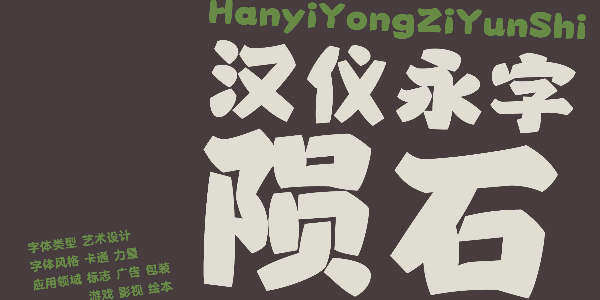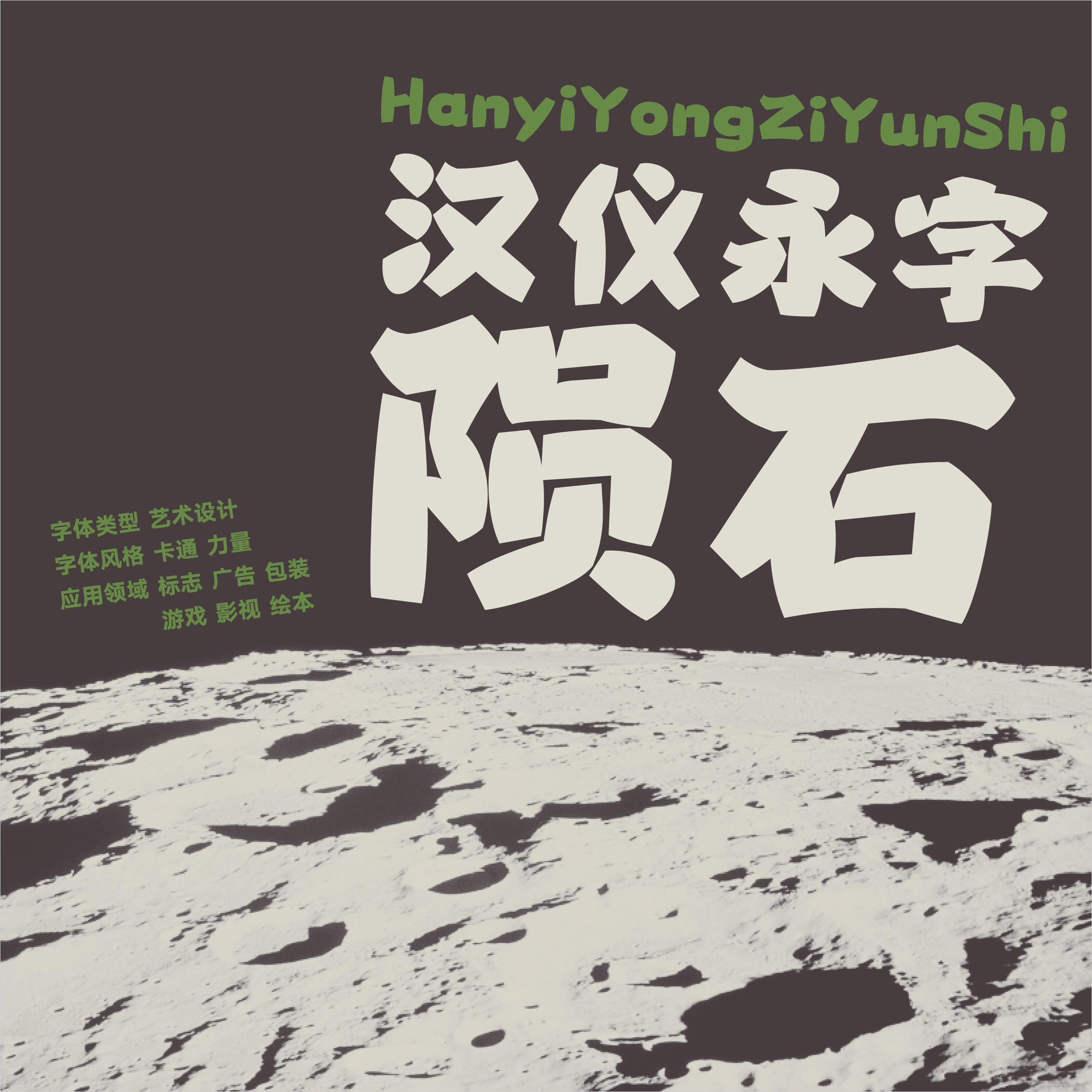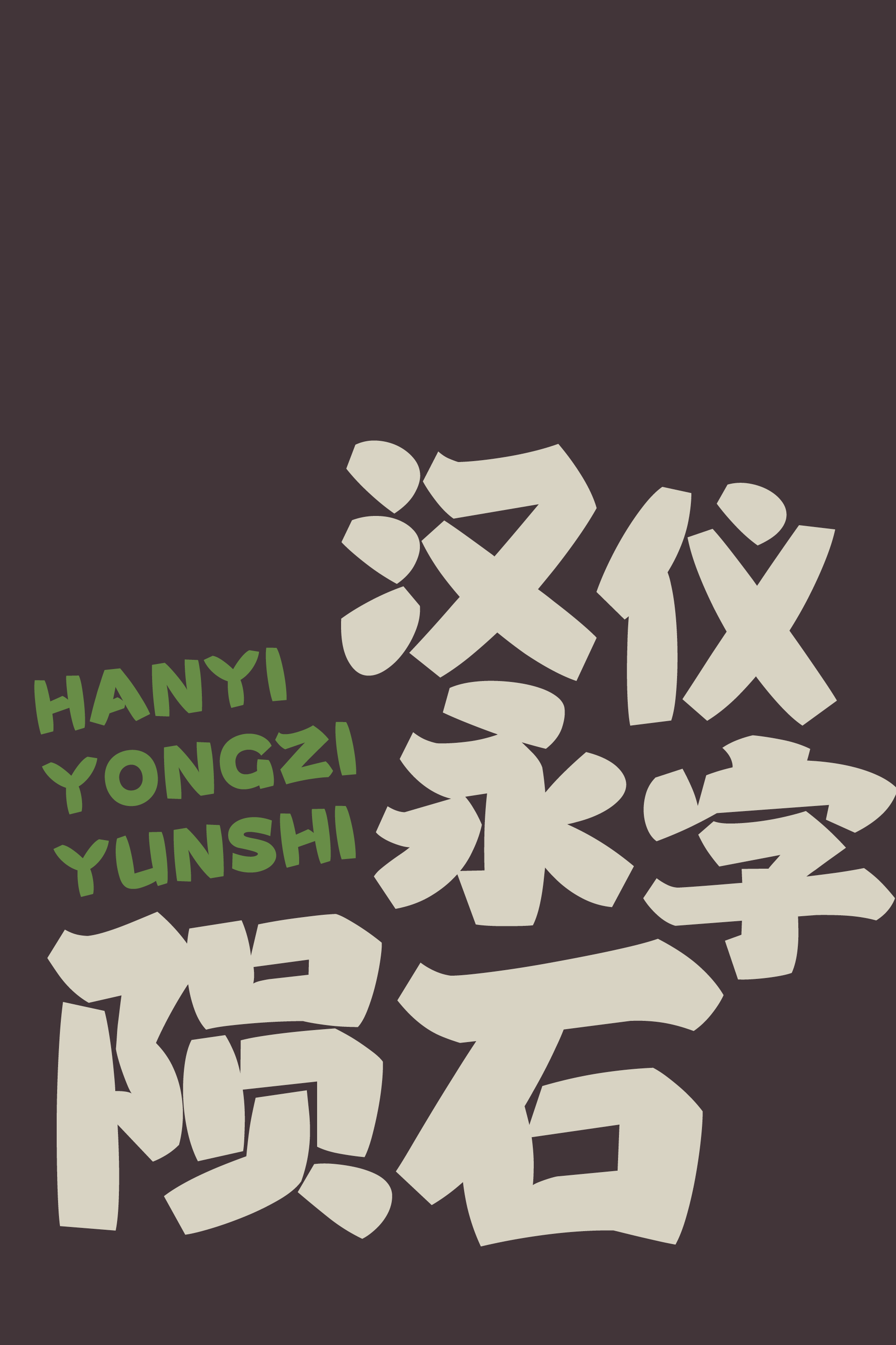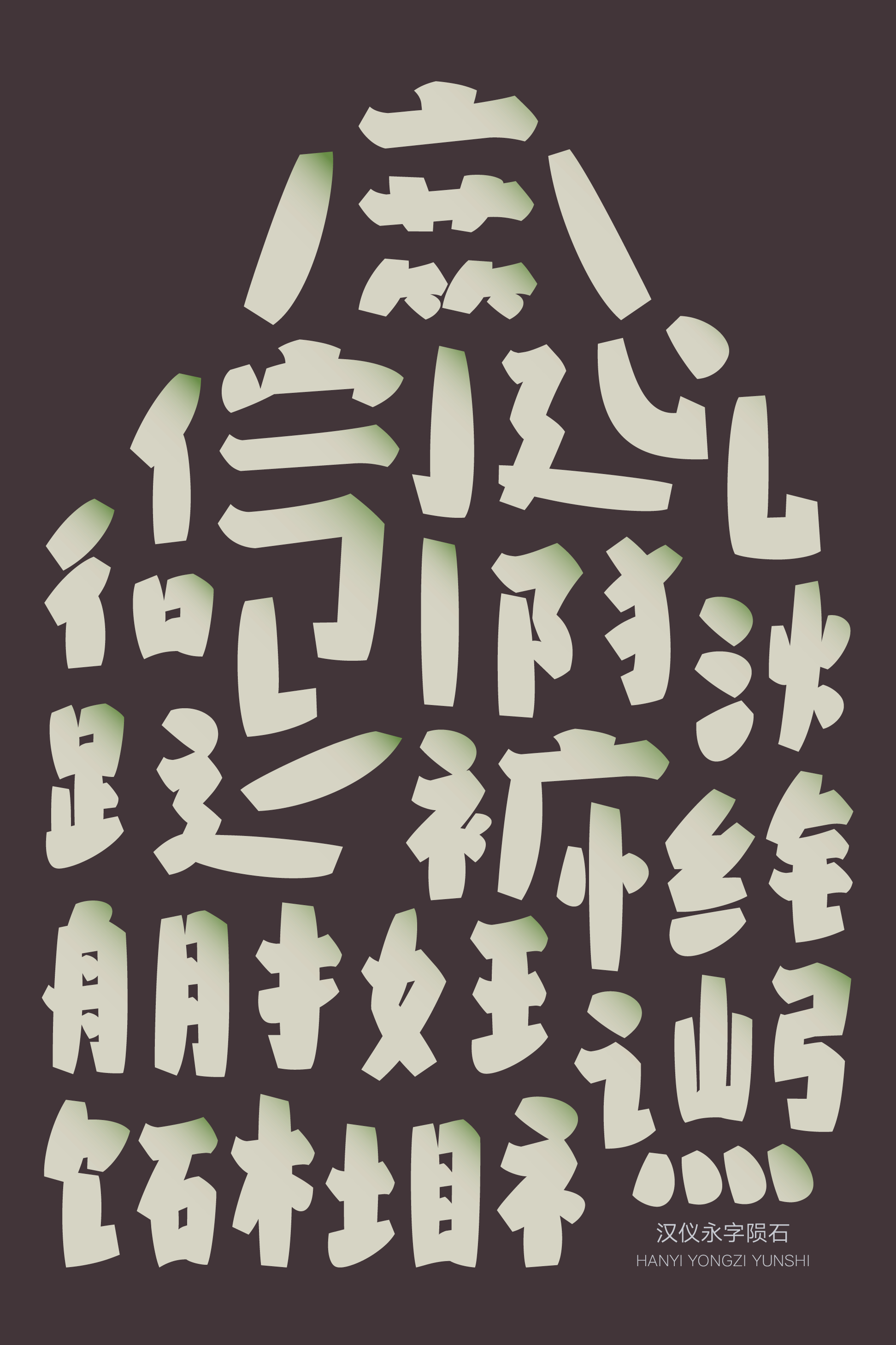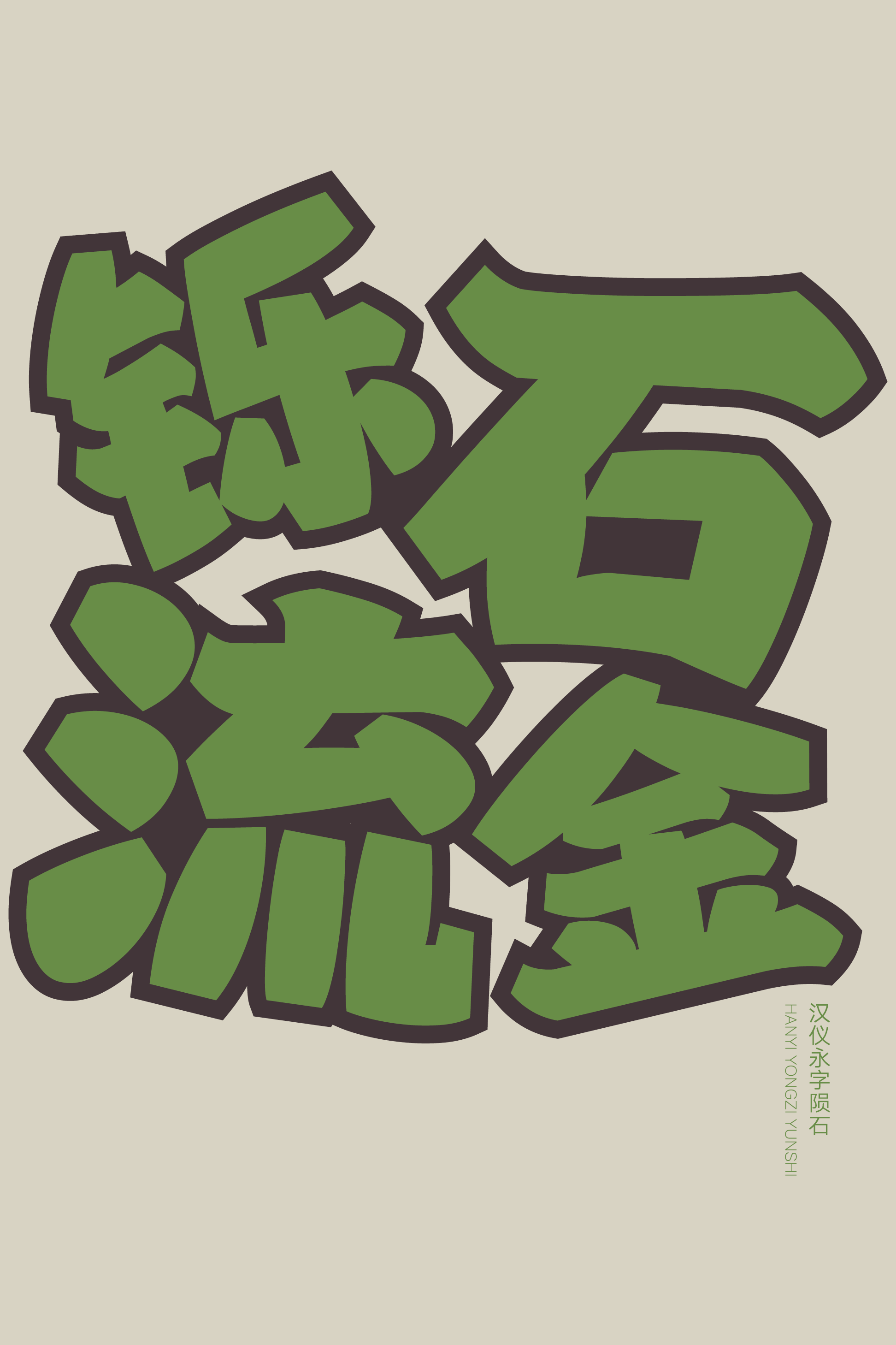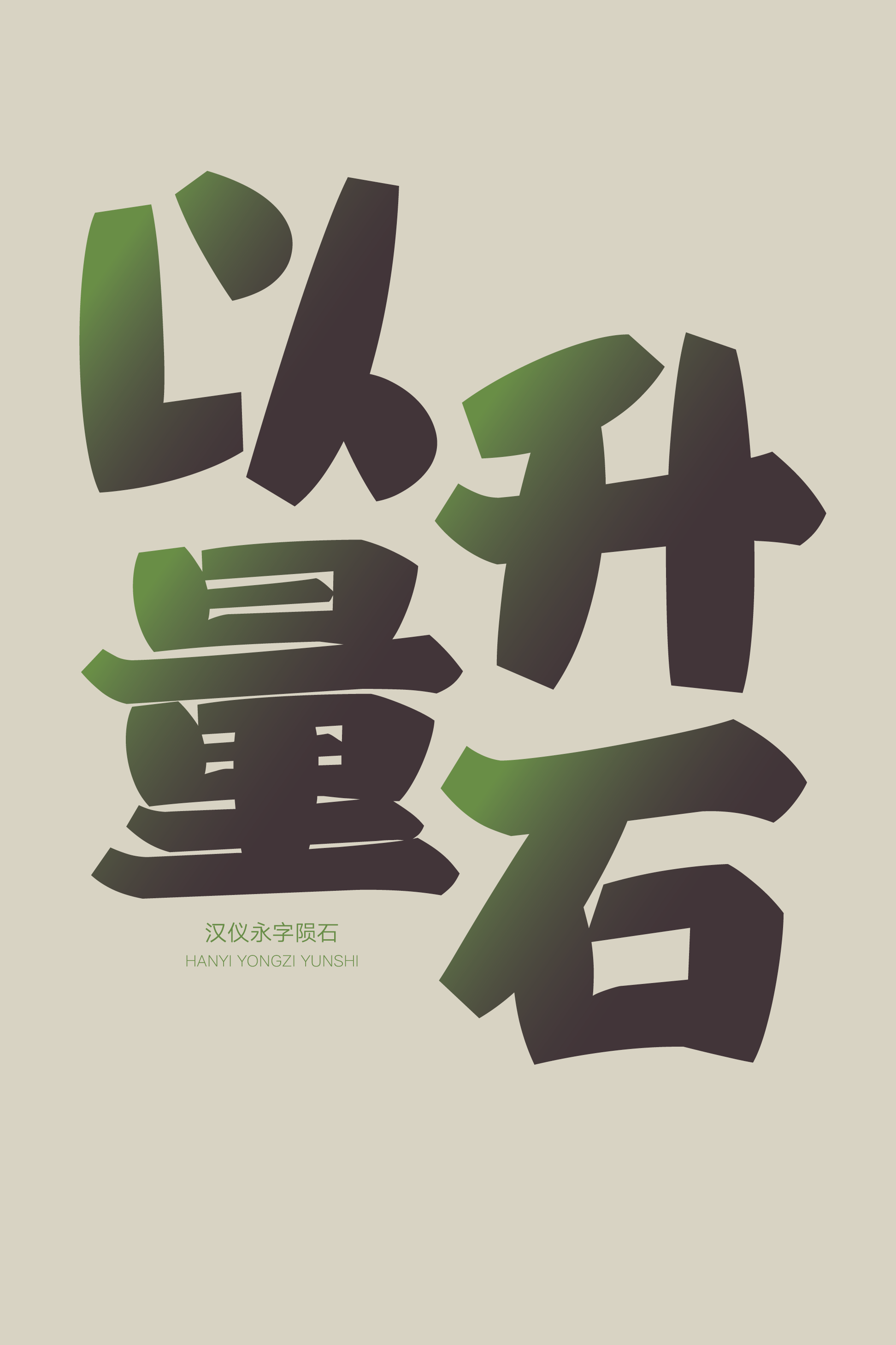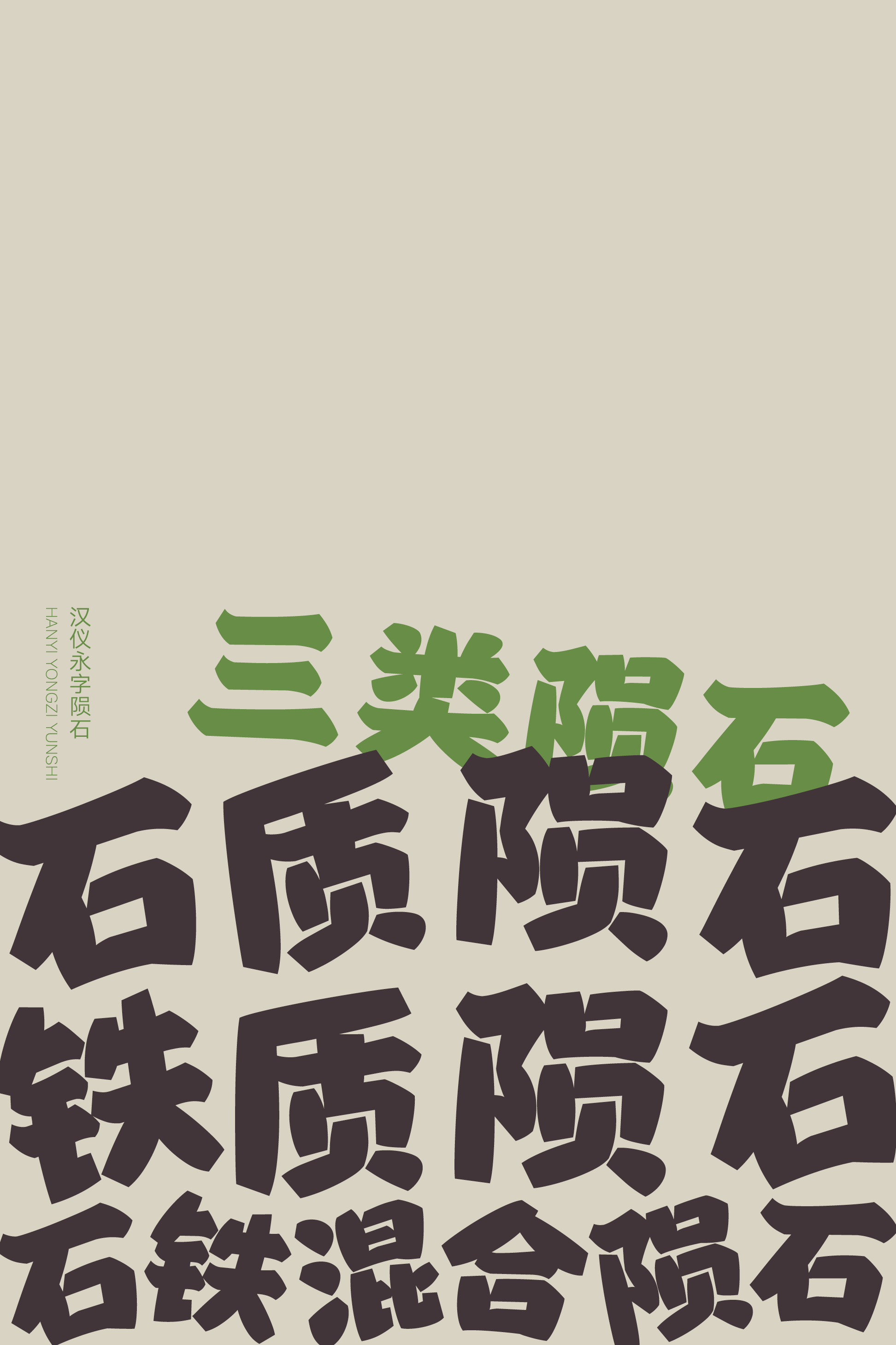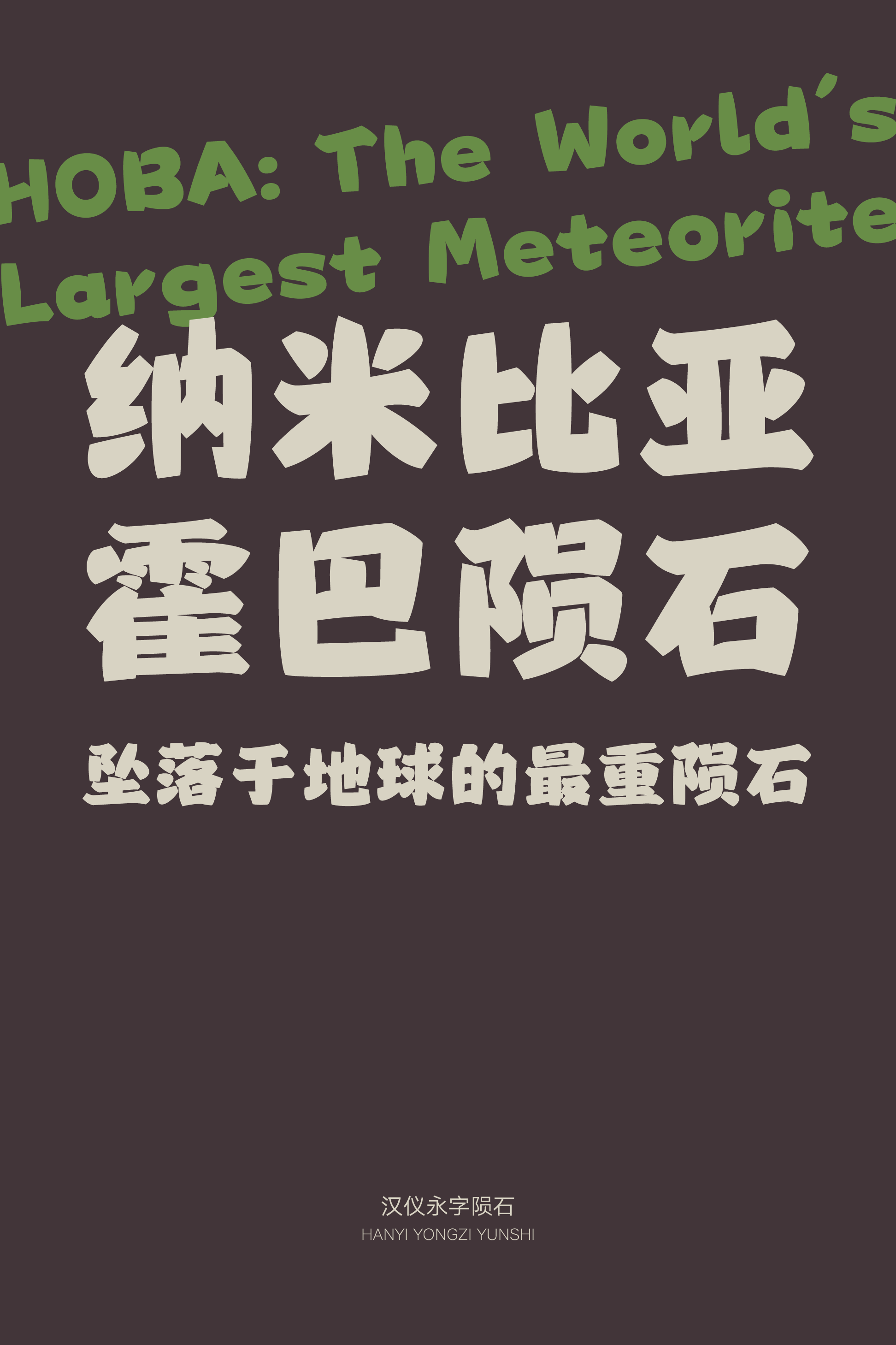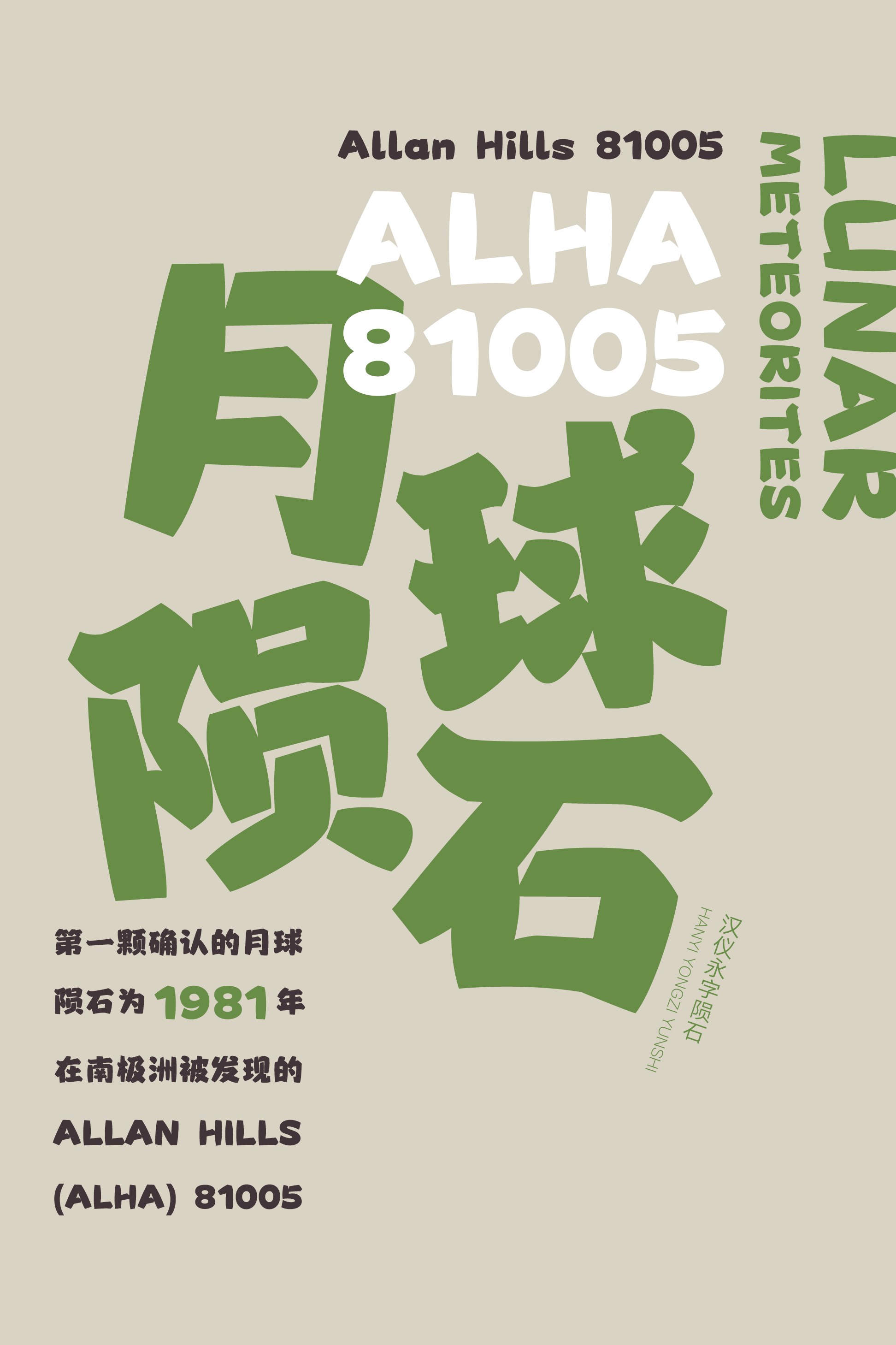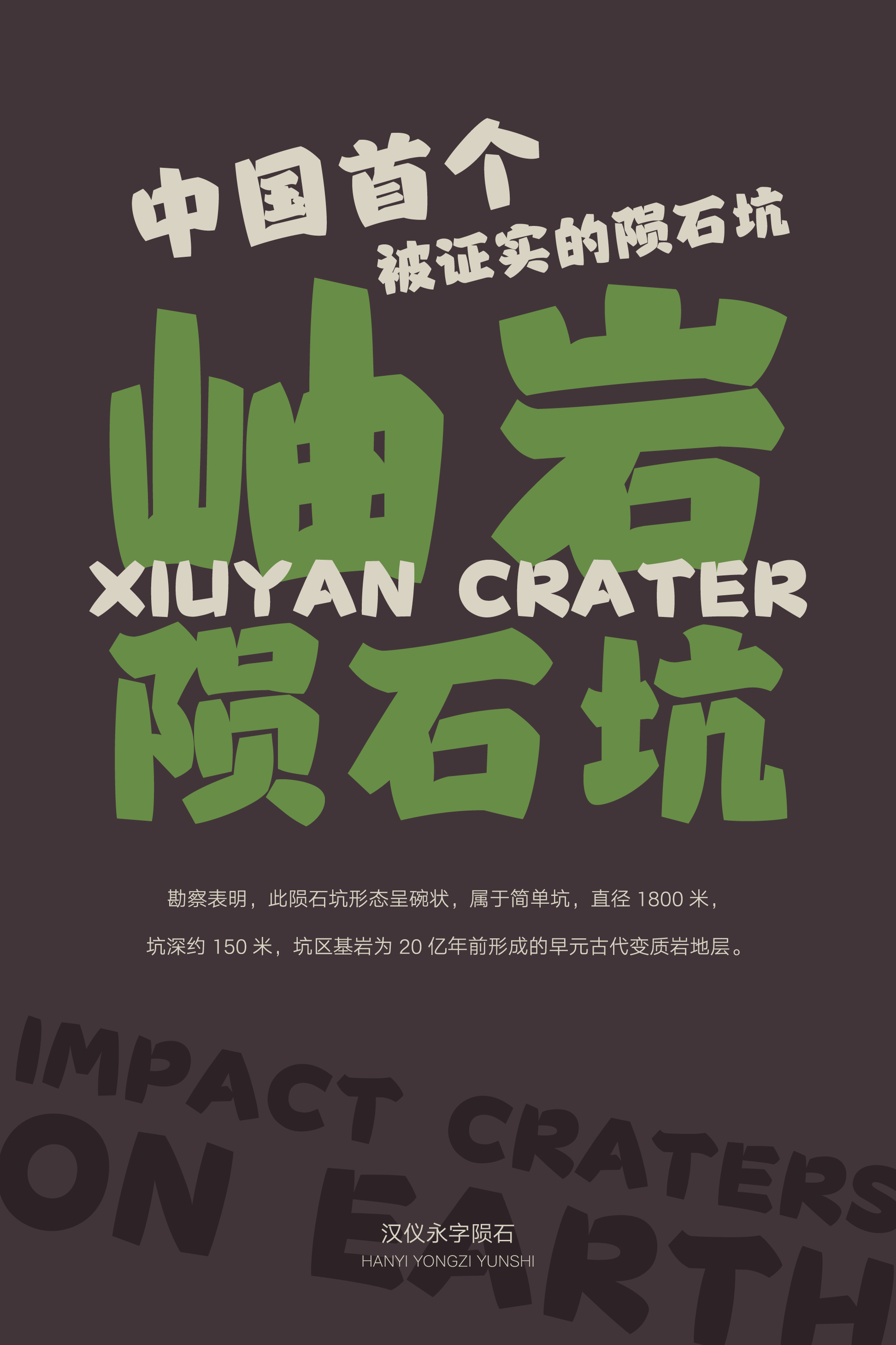
汉仪永字陨石
汉仪永字陨石是由永字社创作的一款掷地有“坑”的标题字体。块面感的造型如同撞击地表的陨石,笔画有重量,粗厚坚实,圆鼓鼓的膨胀感中和了冰冷坚硬的棱角,让这款字体更具卡通色彩。
这款玩味十足的标题字体适用于儿童绘本、少儿图书、趣味科普、玩具包装、电商广告、影视娱乐等使用场景,带来陨石撞击地表的视觉冲击力。
块面感的造型如同撞击地表的陨石,分量十足。
重心稳定,略微偏低,呈现坠落的视觉效果。
不整齐的边缘形成自然的排版肌理。
重量级的笔画粗厚坚实,圆鼓鼓的膨胀感中和了冰冷坚硬的棱角。
笔画断连的设计表现出陨石表面的残损,为满满当当的字形注入空气。
西文部分的造型同样具有陨石一样的块面感和重量感,膨胀圆厚的笔画有着方硬棱角,中西文匹配风格一致。
这款掷地有“坑”的标题字体广泛适用于儿童绘本、少儿图书、趣味科普、玩具包装、电商广告、影视娱乐等使用场景,带来陨石撞击地表的视觉冲击力。